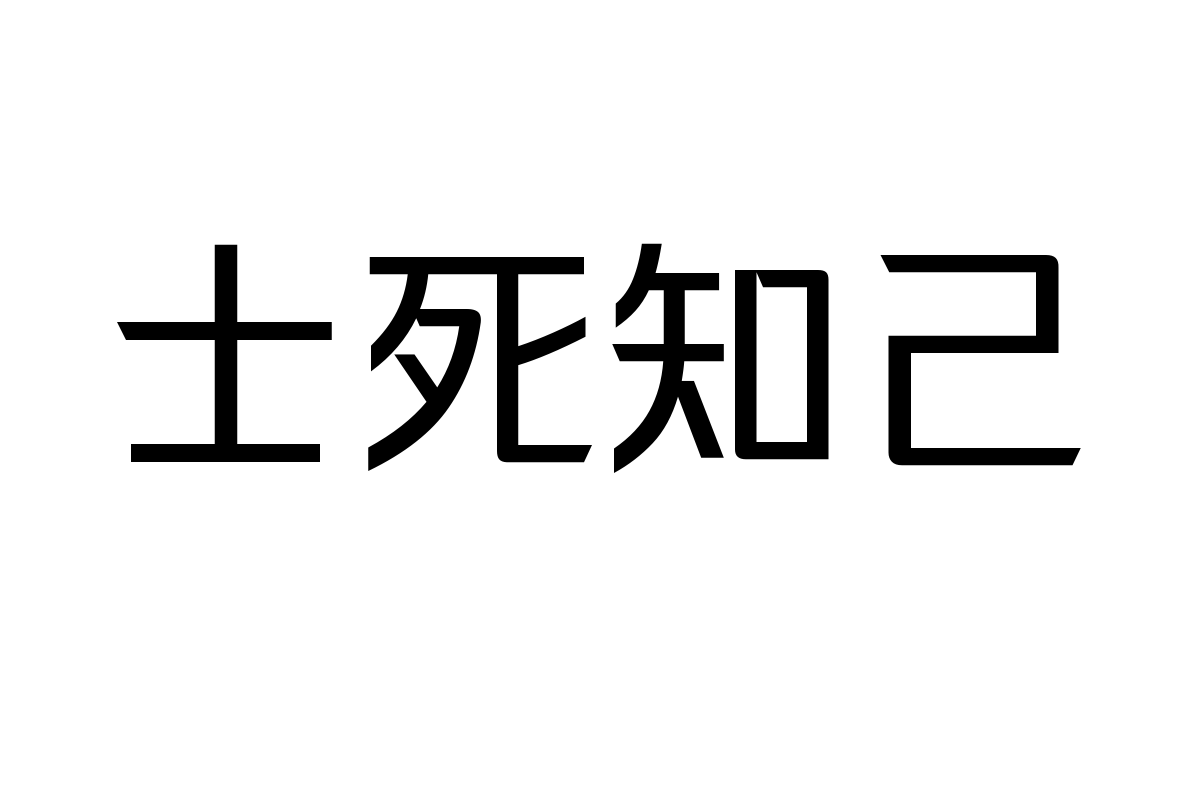
锐字龙书驰黑准粗是一种具有独特风格和特色的字体,它以简洁、清晰和有力的线条为特点,适合用于各种需要突出文字效果的场合。这种字体的特点是:
1. 字形结构紧凑:锐字龙书驰黑准粗的字形结构紧凑,线条流畅,给人一种简洁明快的感觉。
2. 笔画粗细适中:该字体的笔画粗细适中,既不过于纤细,也不过于粗壮,使得整个字形看起来既美观又实用。
3. 笔划方向明确:锐字龙书驰黑准粗的笔划方向明确,无论是直线还是曲线,都呈现出一种自然流畅的美感。
总之,锐字龙书驰黑准粗是一种非常适合用于各种需要突出文字效果的场合的字体,它的简洁、清晰和有力的线条特点使其在众多字体中脱颖而出。